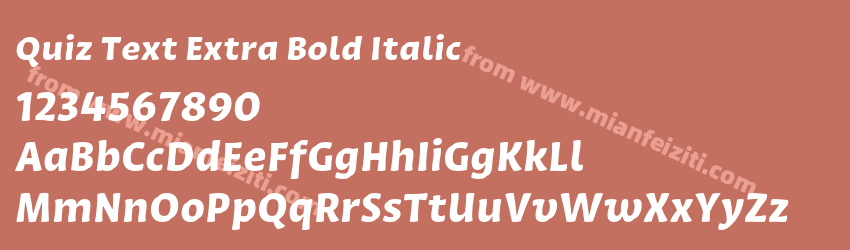
Quiz Text Extra Bold Italic
字体名称: Quiz Text Extra Bold Italic
Postscript名称: QuizText-ExtraBoldItalic
本款“Quiz Text Extra Bold Italic”是一款书写很新颖的字体,字体大方,适合各种设计作品使用!欢迎下载!